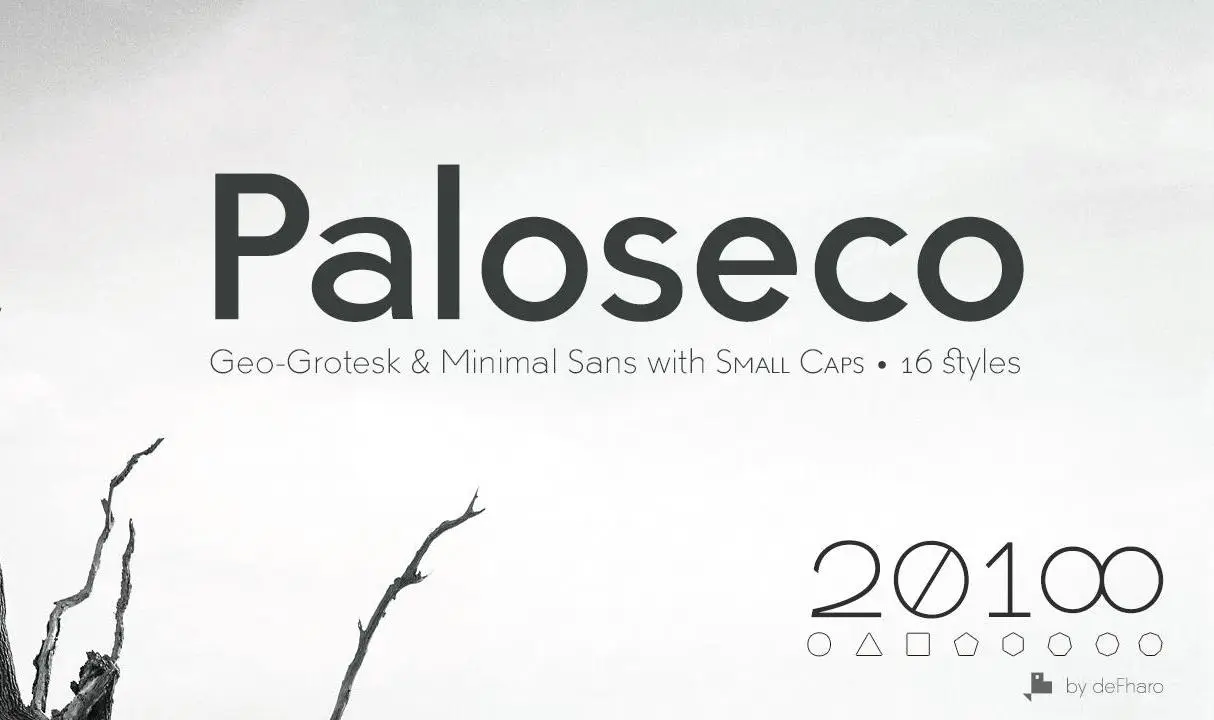
A Paloseco é uma família tipográfica de tipo livre que combina a estética do estilo Geo-Grotesque com os atributos geométricos e minimalistas de uma tipografia moderna, ou “neo-grotesca”. Este conjunto abrange 8 pesos diferentes da fonte, bem como as versões em itálico. As letras pequenas alinhadas estão presentes em todas, além dos símbolos monetários digitais, que permitem um uso ainda mais dinâmico e variado para a Paloseco. A Paloseco é uma tipografia geometricamente perfeita, com modulações neo-grotescas que a fazem imbuída de modernidade e simplicidade. O design inclui alternativas de letras e números, permitindo maior versatilidade nas criações. As pequenas caixas, um recurso que se tornou cada vez mais importante para leitura em formatos digitais, estão presentes também nesta fonte. Além disso, a Paloseco oferece uma configuração meticulosa dos parâmetros de proporção, métrica e kerning (a distância entre as letras), garantindo que qualquer texto seja lido com máxima precisão e clareza, em qualquer tamanho ou formato. Estas características combinadas tornam a Paloseco uma escolha excelente para designers que valorizam um estilo clean e geometricamente preciso, além de versatilidade para usos comerciais como símbolos monetários digitais.